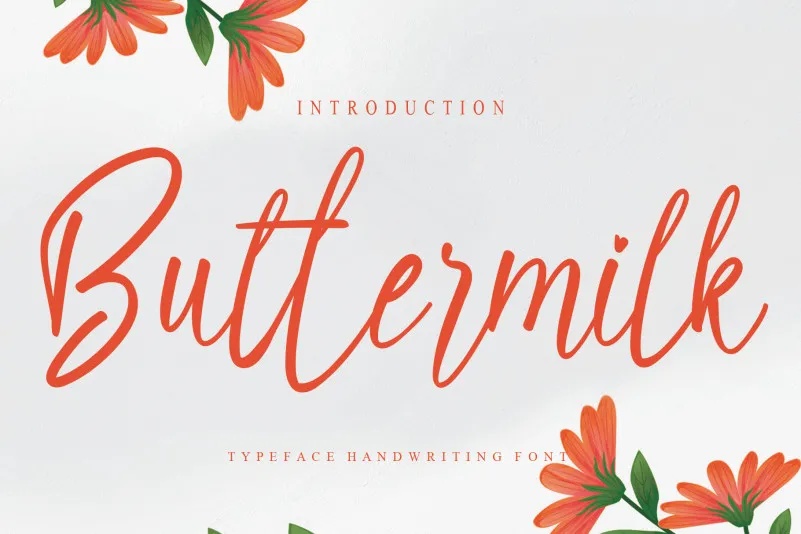
Buttermilk Script Font
A fonte Buttermilk Script é uma escolha perfeita para quem procura algo autêntico e natural na sua próxima criação visual. Embora possa parecer simples, com suas linhas delicadas e texto cuidadosamente escritos à mão, essa fonte oferece um toque sofisticado e elegante que pode ser a diferença entre um design profissional ou não tão profissional quanto gostaríamos de ver. Cada traço é meticulosamente detalhado, criando uma sensação de conforto e familiaridade – algo que agradará aos designers em busca de uma fonte versátil que se adequa perfeitamente tanto para materiais publicitários quanto para editoriais. Através da autêntica natureza do seu design, esta font pode transformar o simples texto em um elemento vibrante e único no centro de qualquer projeto visual. Criado por creativletter, a Buttermilk Script é uma mão-de-obra cuidadosa que transmite uma sensação de confiança com seu aspecto elegante. Não importa se você está criando um site pessoal ou trabalhando em uma campanha publicitária global, a fonte Buttermilk Script pode contribuir para a sua criação tornar-se ainda mais memorável. Com este design cuidadosamente elaborado à mão, você estará seguro de que cada detalhe do seu projeto será o ponto de destaque.